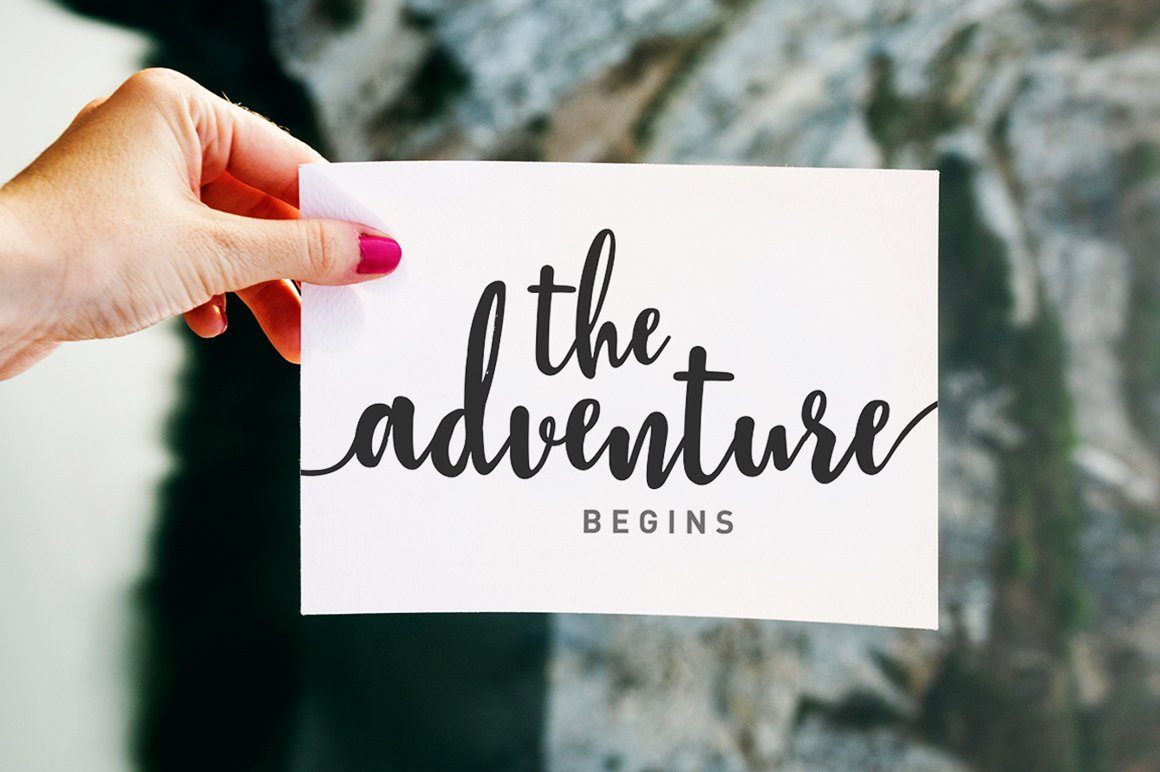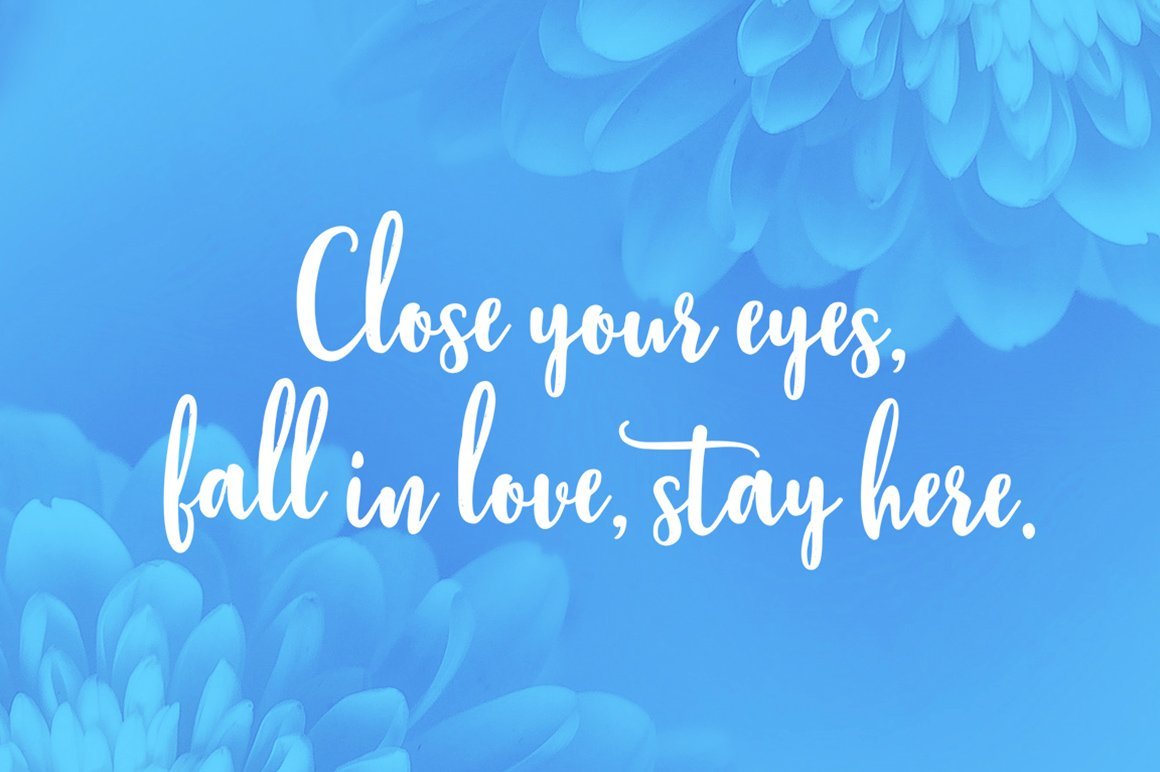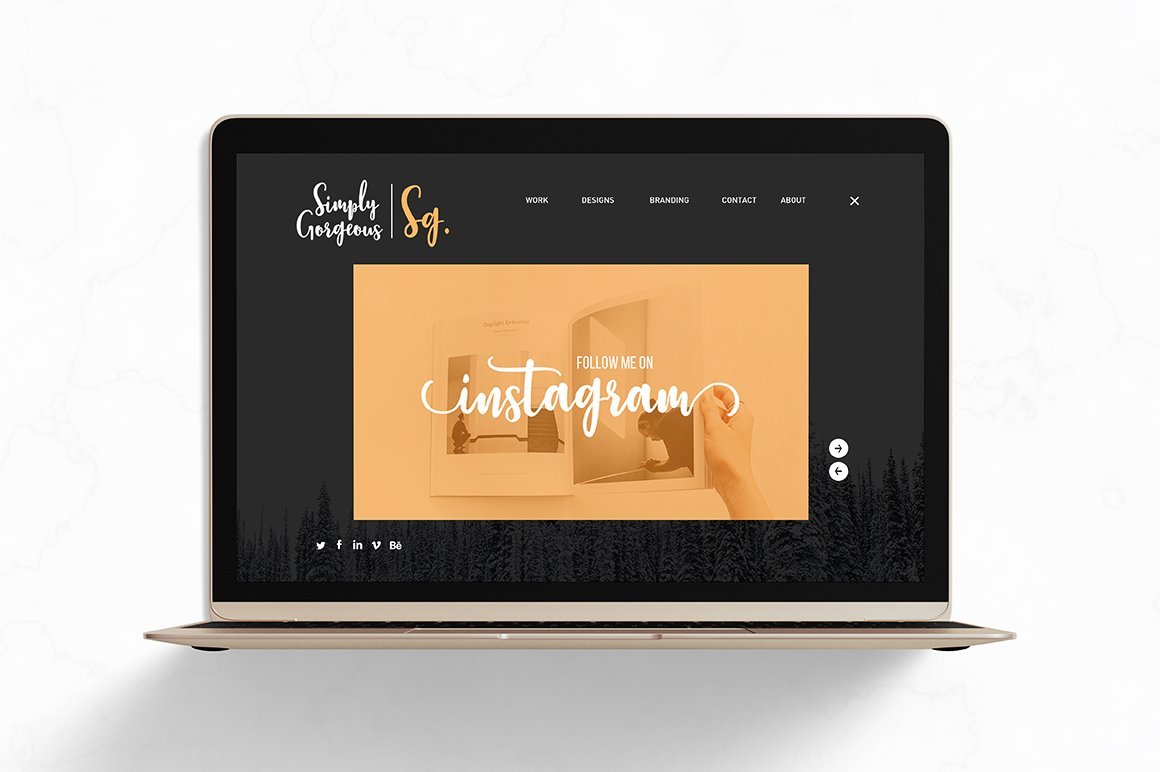
About Stephanie Script
Stephanie Script adalah font skrip modern baru dengan garis dasar tidak beraturan. Bergaya trendi dan feminin. Stephanie terlihat cantik di undangan pernikahan, kartu ucapan terima kasih, kutipan, kartu ucapan, logo, kartu nama dan banyak lagi. Sempurna untuk digunakan dalam tinta atau cat air. Termasuk huruf awal dan terminal, alternatif, ligatur, dan dukungan berbagai bahasa. To enable the OpenType Stylistic alternates, you need a program that supports OpenType features such as Adobe Illustrator CS, Adobe Indesign & CorelDraw X6-X7, Microsoft Word 2010 or later versions. There are additional ways to access alternates/swashes, using Character Map (Windows), Nexus Font (Windows), Font Book (Mac) or a software program such as PopChar (for Windows and Mac).How to access all alternative characters: https://www.youtube.com/watch?v=Go9vacoYmBw https://www.youtube.com/watch?v=XzwjMkbB-wQ https://www.youtube.com/watch?v=x1A_ilsBsGs https://www.youtube.com/watch?v=xFlMwARHusY Thanks so much for looking and please let me know if you have any questions.